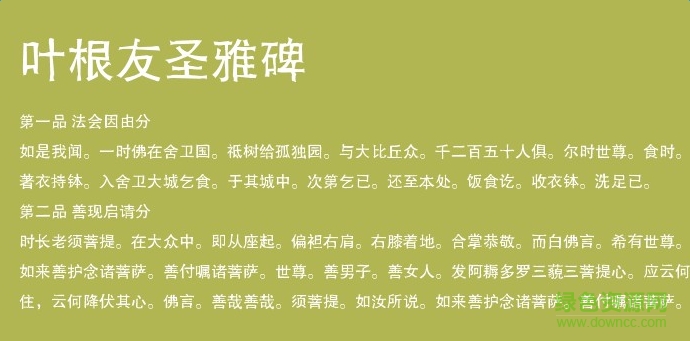
葉根友圣雅碑字體是一款古典文雅風(fēng)格字體軟件,圣雅碑體筆畫非常工整,每個字所占空間一致,所以整體效果比較清爽耐看,在印刷、廣告等方面有著不錯的應(yīng)用,還有更多好看字體歡迎來綠色資源網(wǎng)下載體驗!
葉根友圣雅碑字體在楷體的基礎(chǔ)上添加了一些次要的成分,是的字跡的造型出現(xiàn)神圣的感覺葉根友圣雅碑字體不失圓潤,看上去大方和諧!
全新一代碑體,字體粗細(xì)均勻,非常工整,棱角突出,比較有型!